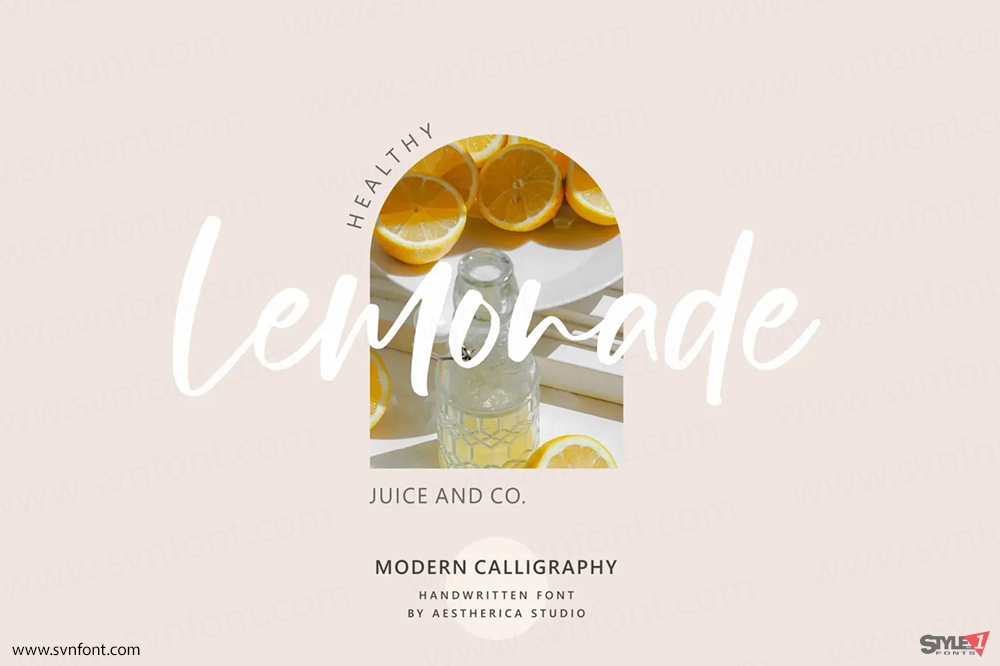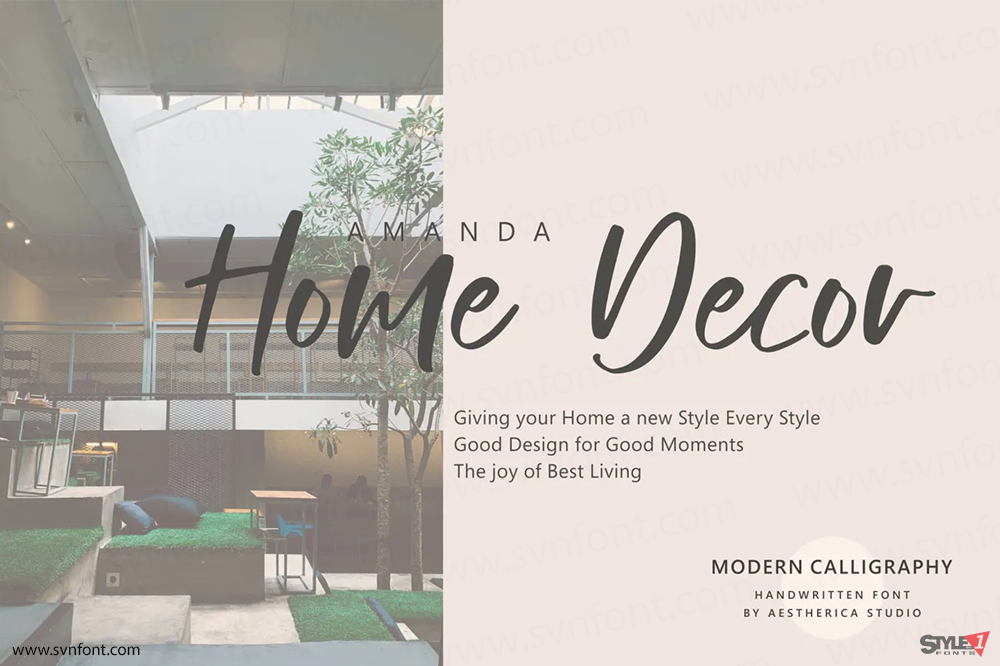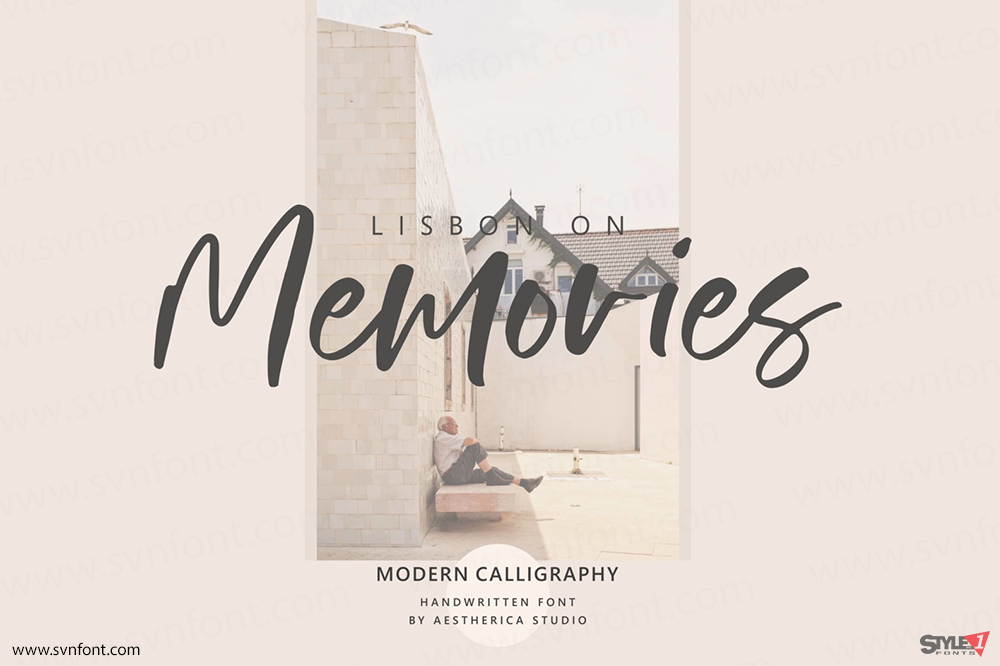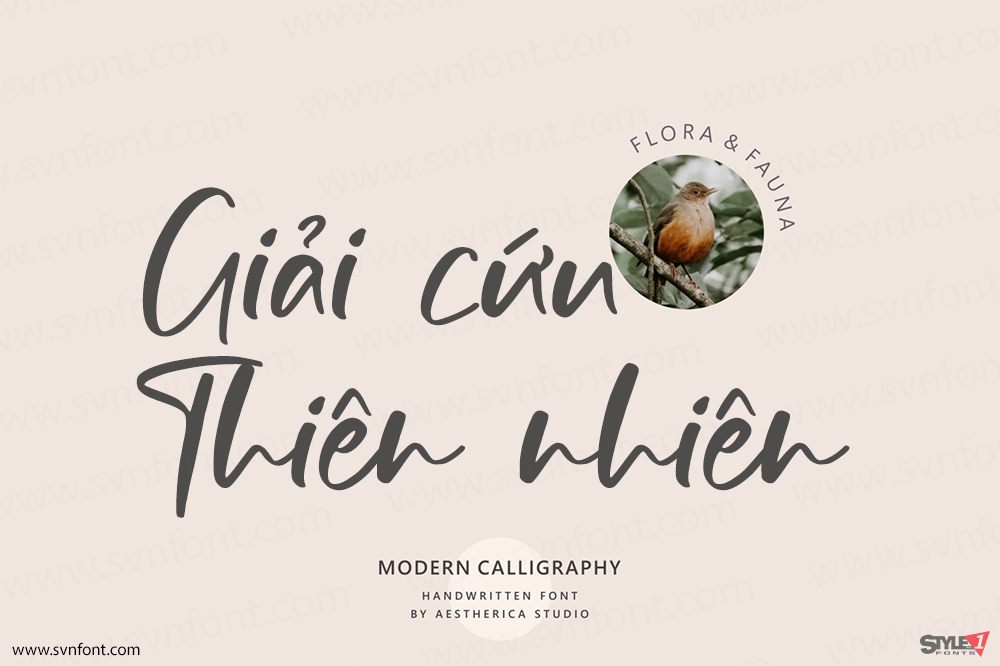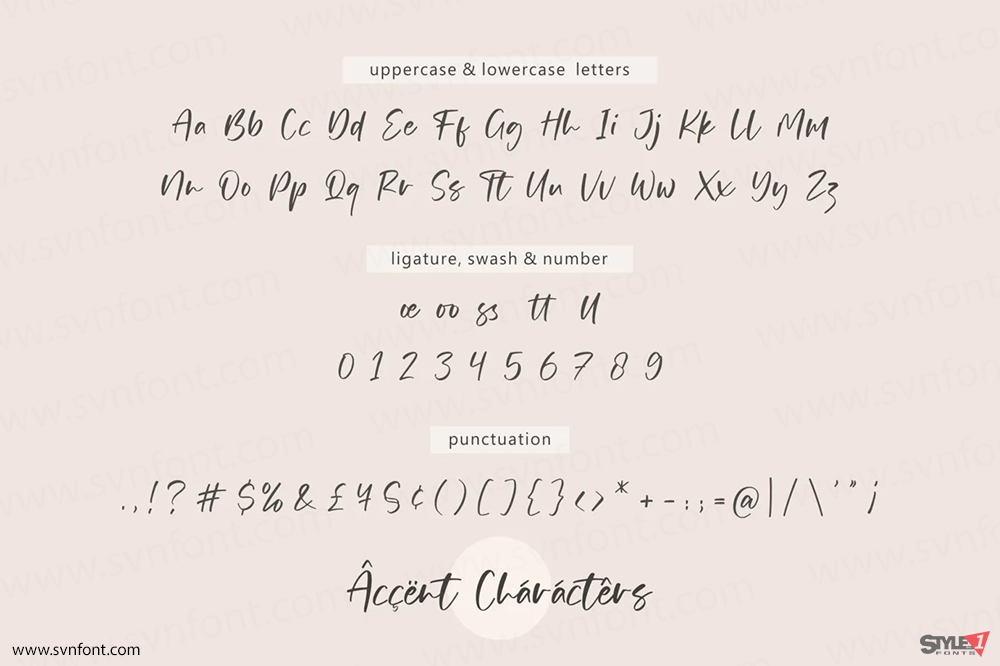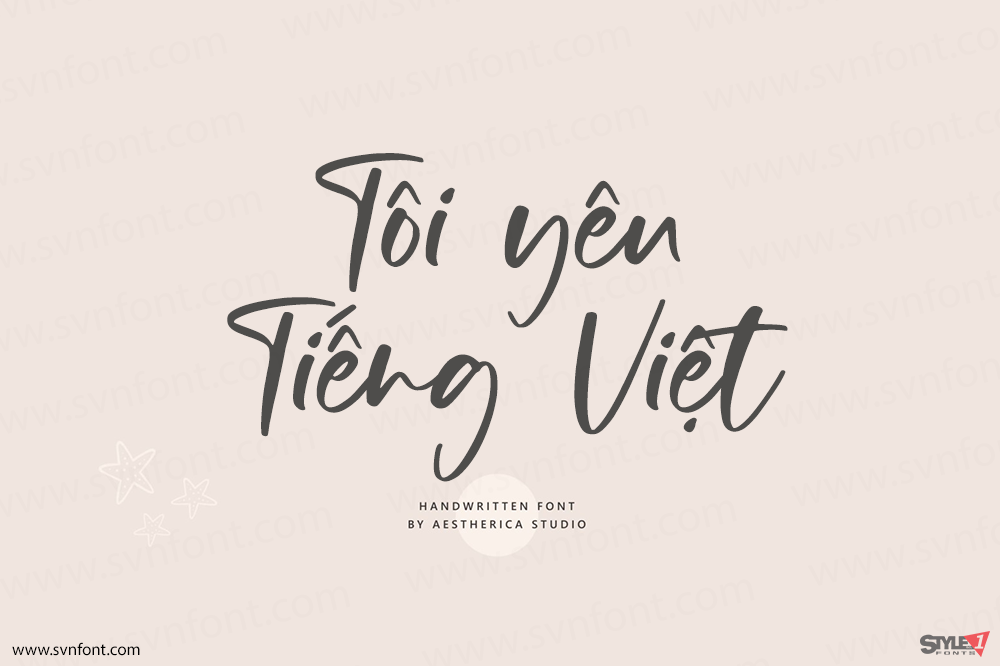
Blooming là một font viết tay hiện đại, hoàn hảo cho các dự án branding, logo, thiết kế cưới, bài đăng mạng xã hội, quảng cáo, bao bì sản phẩm, thiết kế sản phẩm, nhãn mác, nhiếp ảnh, watermark, thiệp mời, văn phòng phẩm và mọi dự án cần cảm giác chữ viết tay tinh tế.
Nhà thiết kế: Aestherica Studio
Nhà phát hành: Aestherica Studio